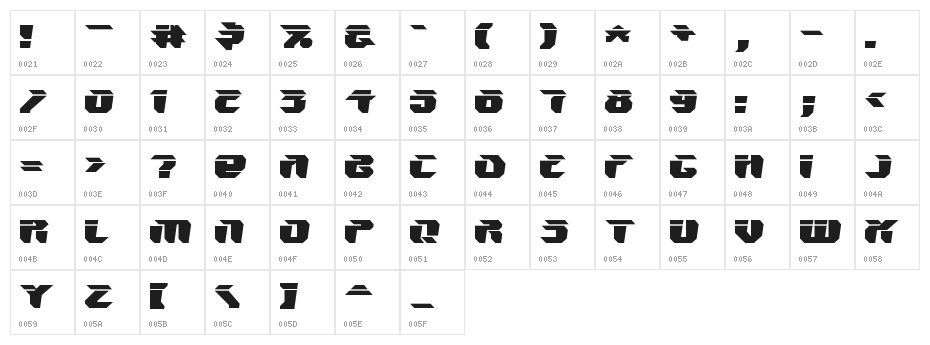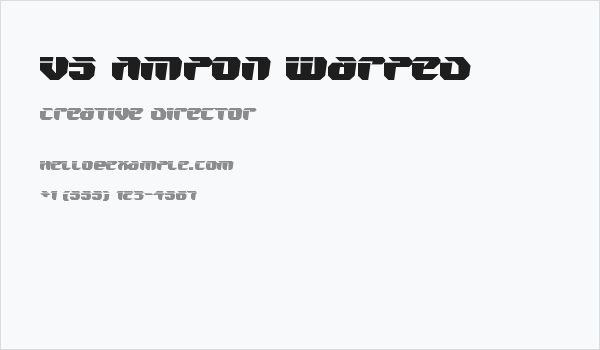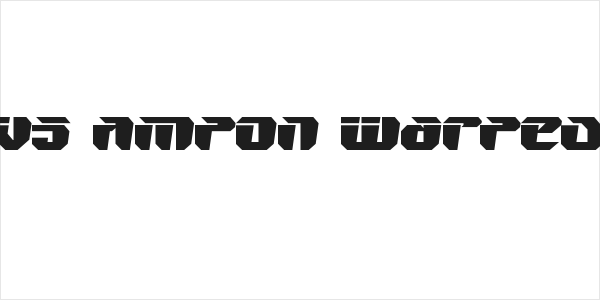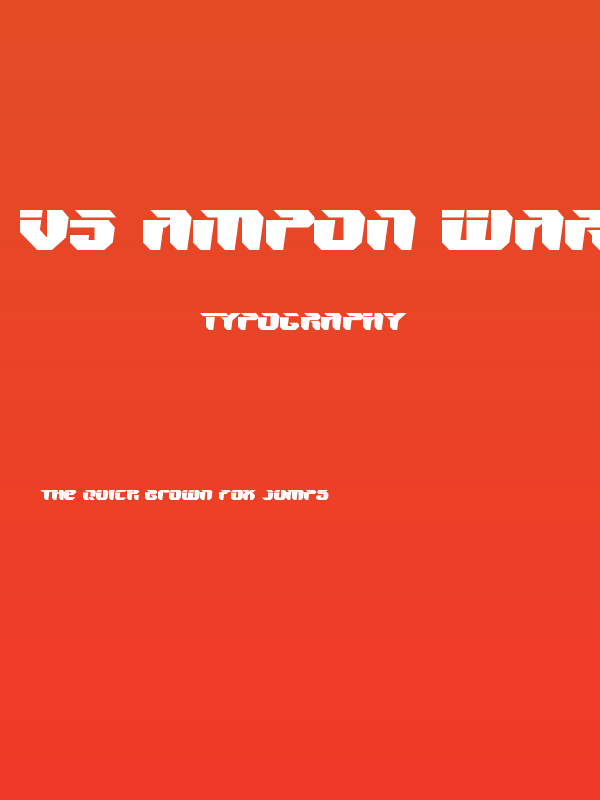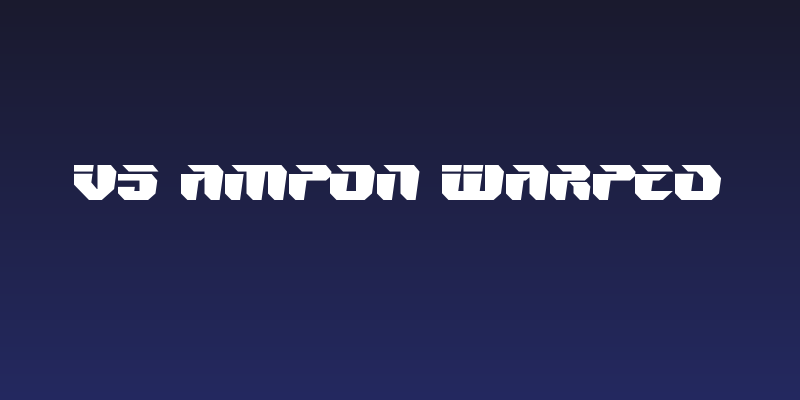
V5 Ampon Warped Font
| Stile generale | Futuristic |
| Progetti proposti | Ideal for sci-fi themed designs, video game titles, tech branding, and modern posters. |